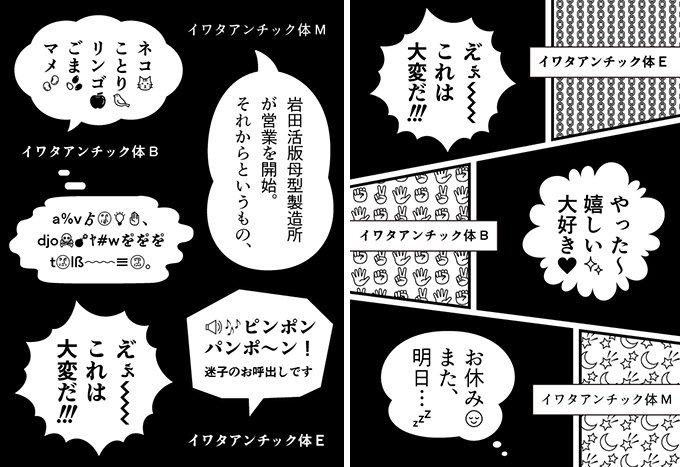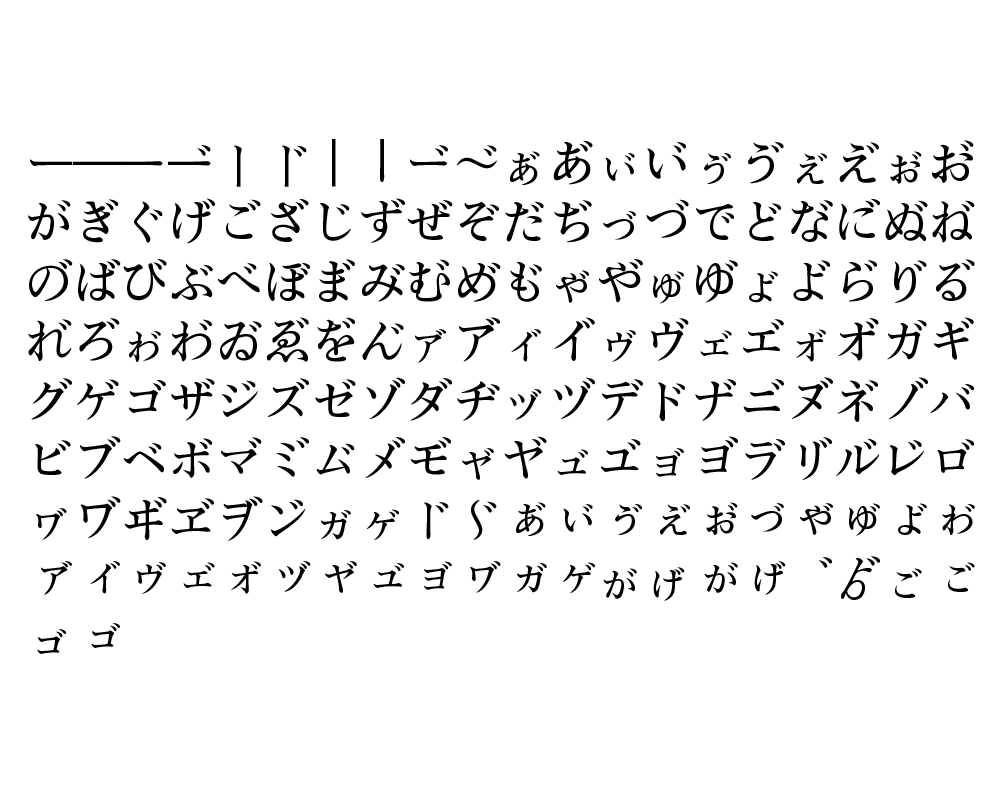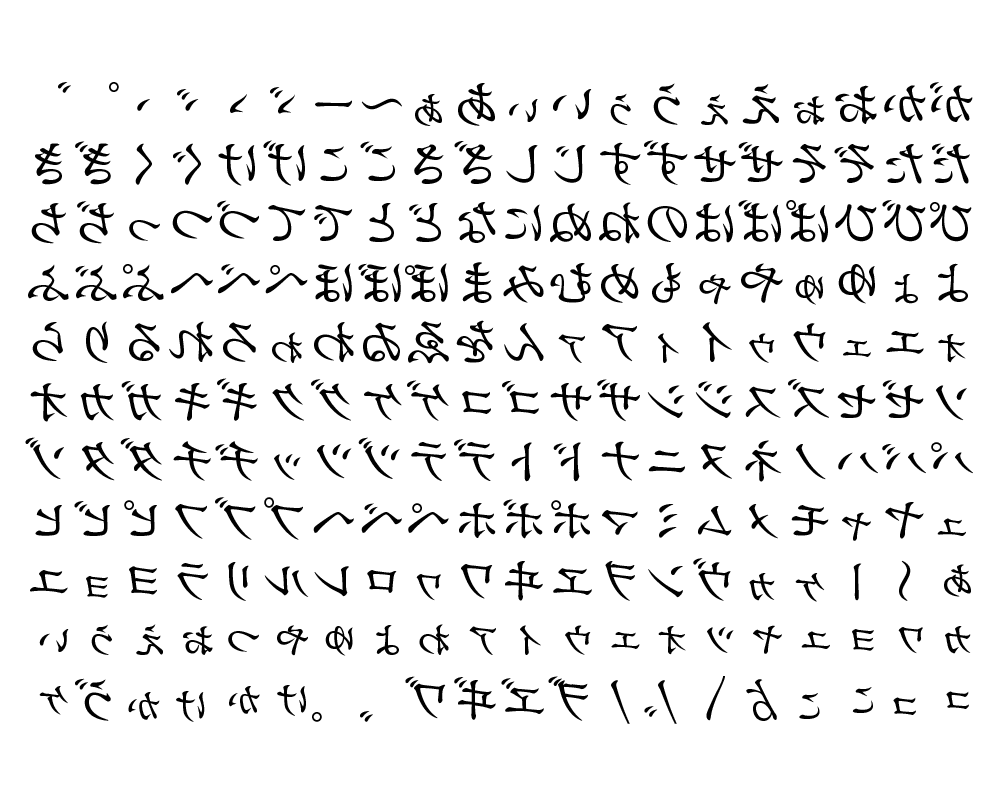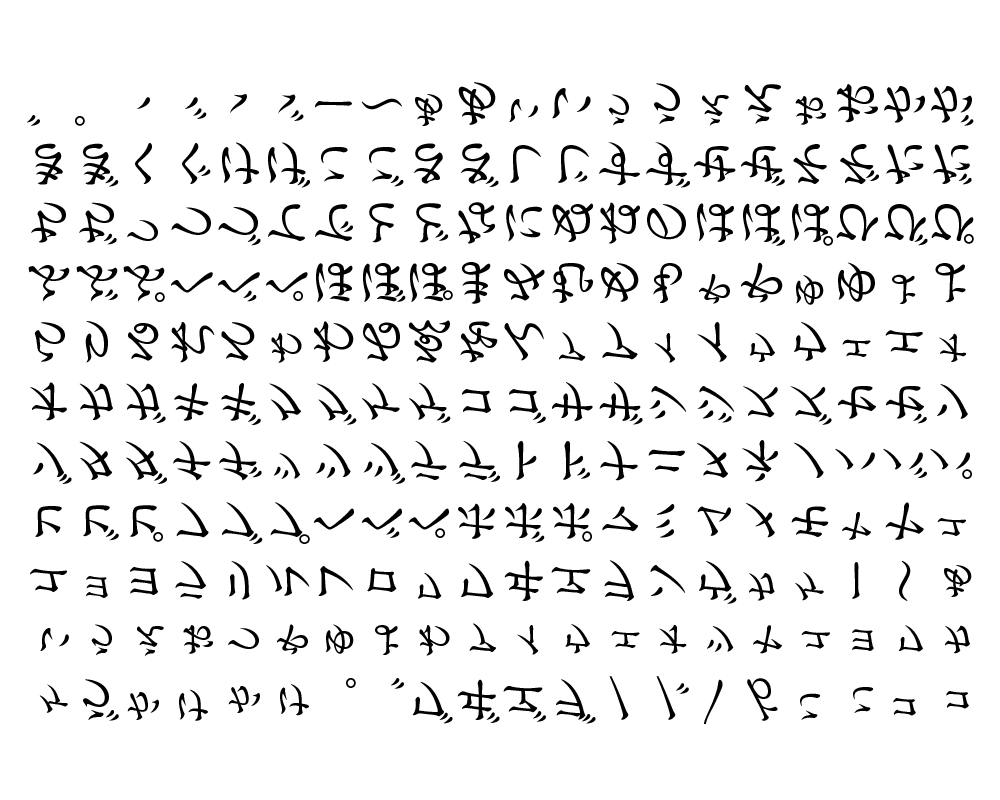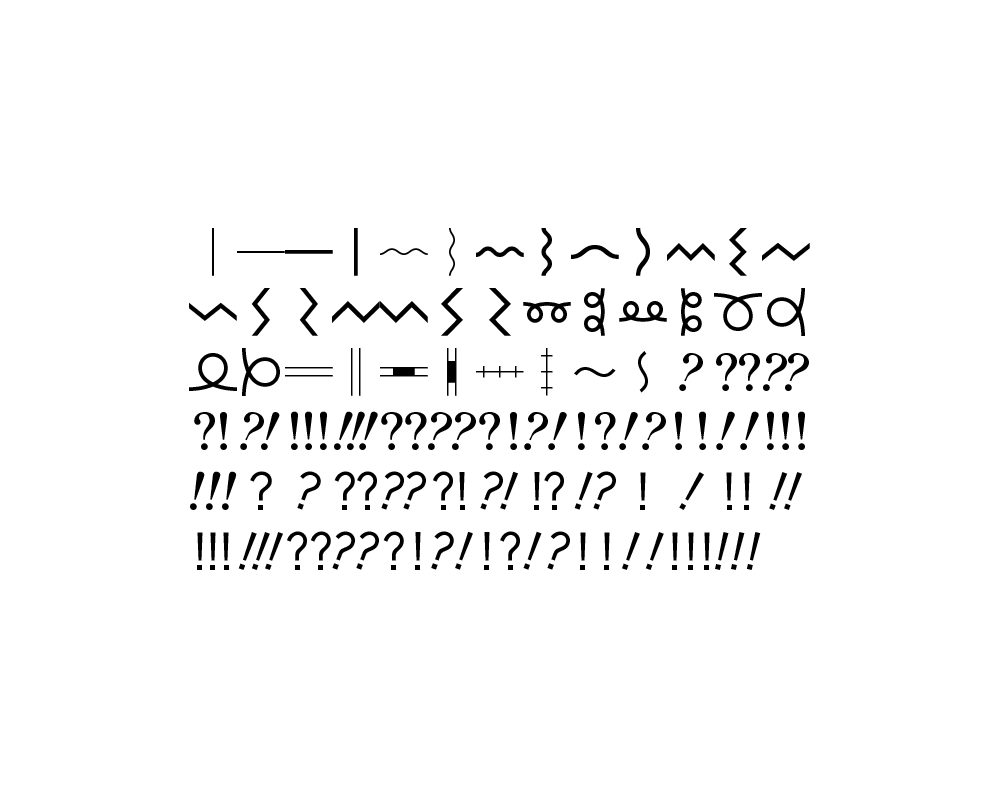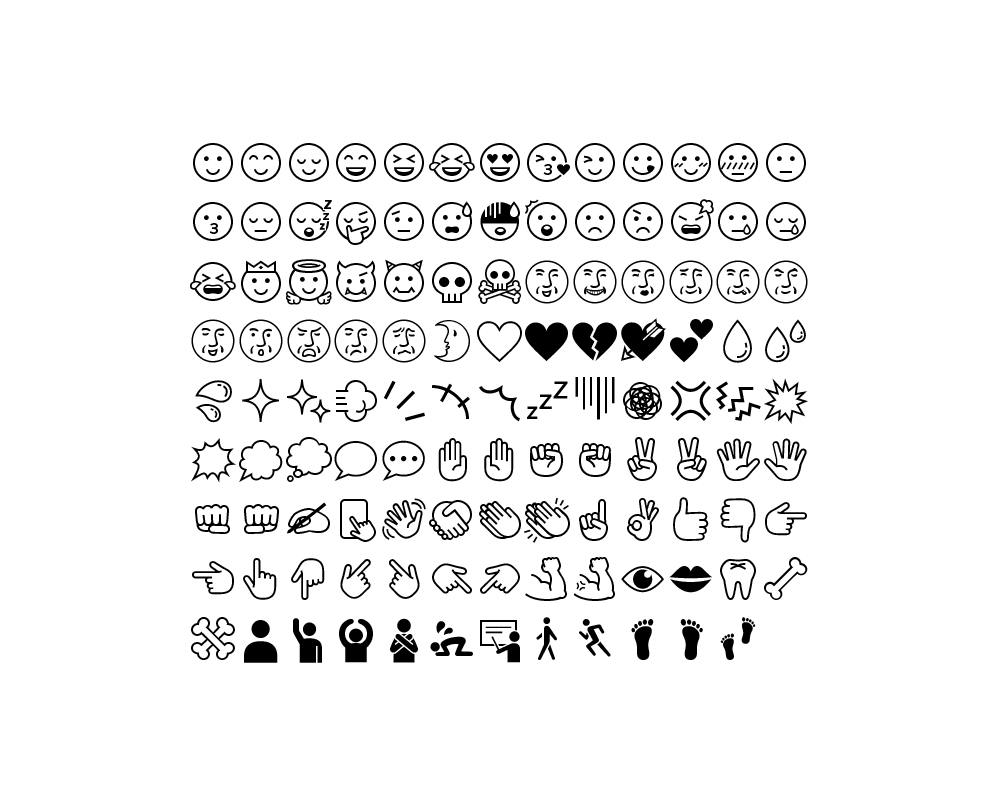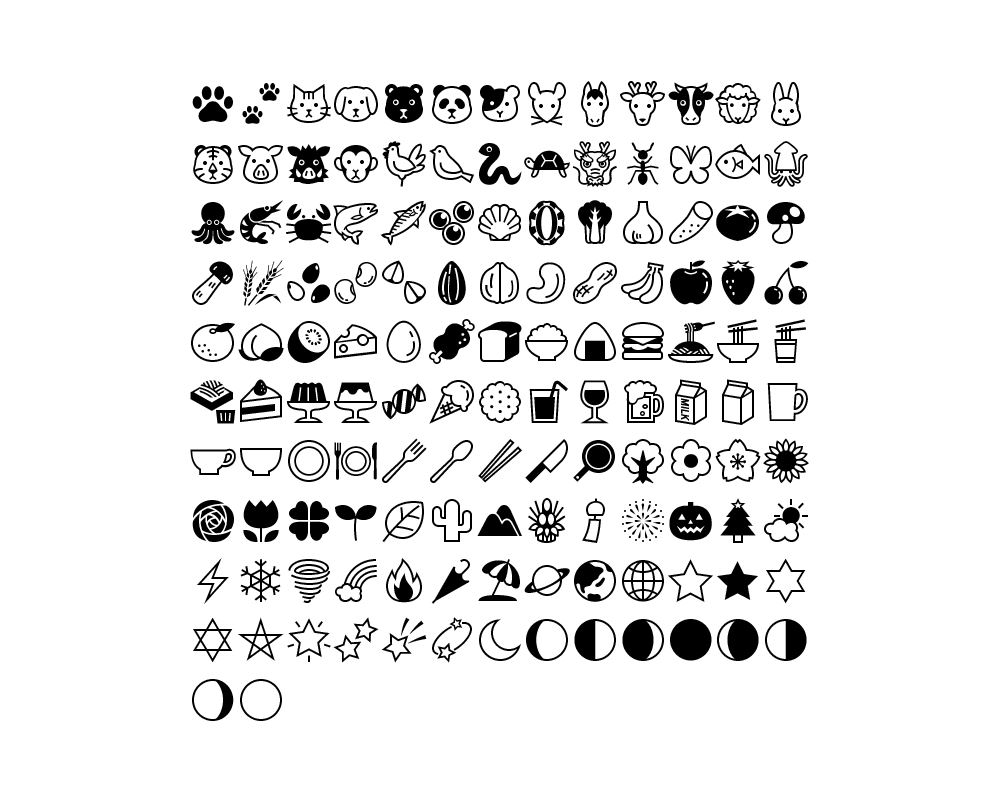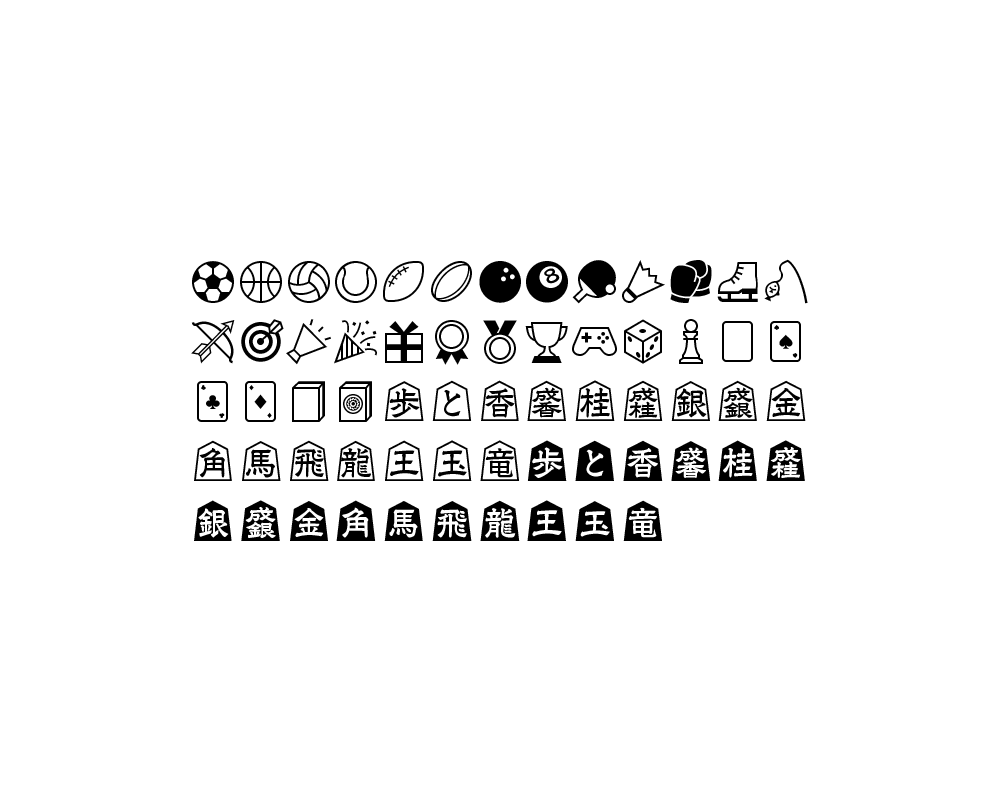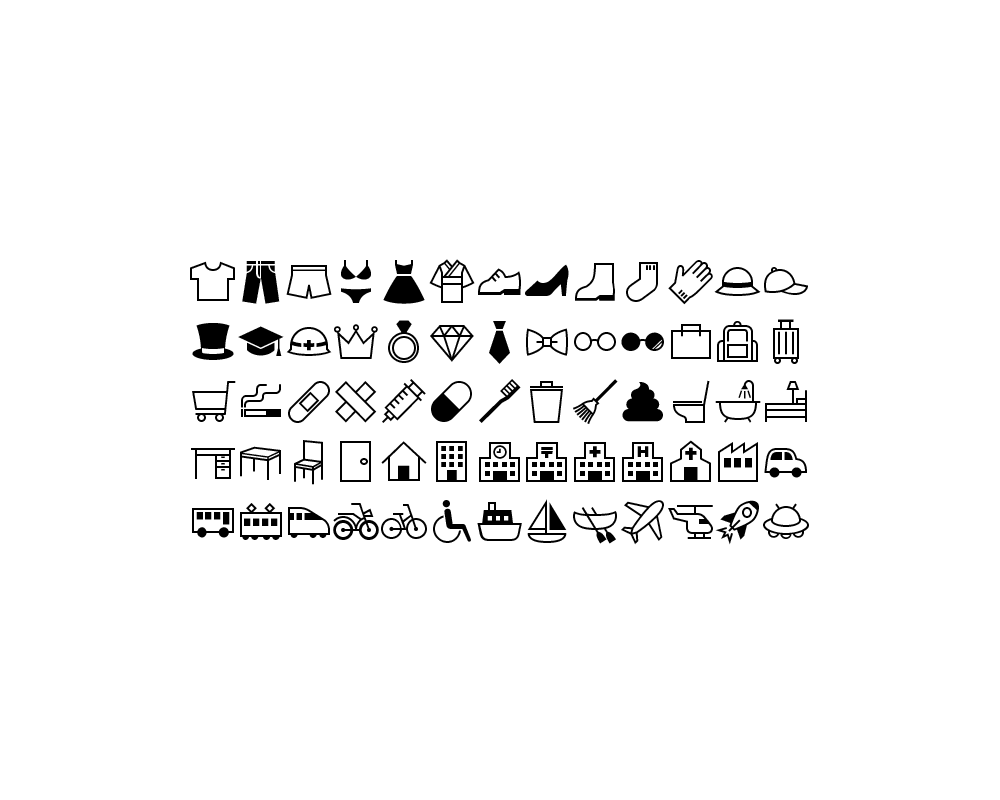
イワタアンチック体ファミリー 同人誌・コミック・映像などに大活躍
同人誌・コミック・映像などで大活躍 新たに外字が追加されたイワタアンチック体
2021年6月に新発売したイワタアンチック体ProNは新たに1,400以上のアンチック外字が追加になりました。特殊な仮名や絵文字・記号類など遊び心に満ちた文字が揃いました。漫画の吹き出からYouTubeのテロップまで様々なエンターテインメントでご活用いただけます。印刷物、同人誌、マンガ、YouTub、動画制作など、創作活動のあらゆる場面でご利用可能です。
イワタアンチック体とは
漫画のふきだしや辞書の見出しに使われるアンチック体は、ゴシック系の漢字に明朝体風の仮名を組み合わせた書体。明朝体に比べると縦横の太みの差が少ないのが特徴です。
イワタアンチック体は、力強いゴシック漢字に筆書き風の柔らかいアンチック仮名を組み合わせて開発され、その表情豊かな書風から漫画の吹き出しなどに多く使われてきました。
仮名に関しては『普通の筆書きの仮名』をコンセプトに、イワタの書体設計士・橋本和夫が描きおろしたもの。それぞれの仮名のもつ固有の形をできるだけ生かし、あえて揃えない『書き文字』の仮名を採用。筆書き風の、少し柔らかい雰囲気をもたせています。
M (中)、B (太)、E (特太) の3ウエイトを揃えることで、媒体や大きさなど多様化する今どきのコミックに対応しました。文字種はAdobe-Japan1-4準拠と大幅に拡張したほか、特殊な仮名や絵文字・記号類など遊び心に満ちた文字をアンチック外字として新規追加しています。同人誌やコミックはもちろん、映像など様々なエンターテインメントに是非ご活用ください。
イワタアンチックProN 外字一覧
イワタアンチックProNシリーズには、表現豊かなセリフを簡単に表現できるユニークな仮名や記号、アンチックに限らずさまざまな場面で活用できる絵文字など、オリジナル外字 1,434字を収録しています。
濁点付きかな
半濁点付きかな
左右反転かな
上下反転かな
音引き・線・!? / 気持ち・顔・体
動物・食べ物・自然 / スポーツ・ゲーム
くらし・建物・乗り物 / 道具
マーク・その他
※ この一覧ではイワタアンチックProN Bを使用しています。(M/Eでは、かな類や線の一部を各フォントに合わせたウェイト別の太さで収録しています)
イワタアンチック体 ProN M
イワタアンチック体 ProN B
イワタアンチック体 ProN E